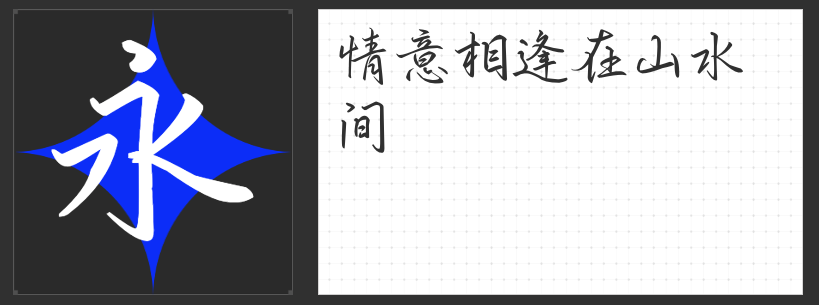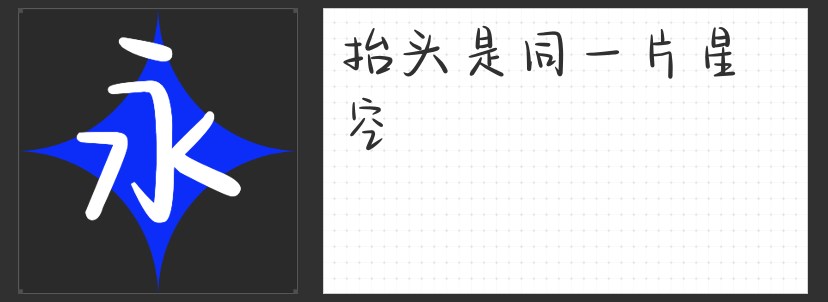
四款电商设计“吸睛利器”:用字体打造视觉记忆点
在电商设计竞争激烈的当下,字体的选择往往成为品牌差异化与视觉吸引力的关键。一款兼具个性与辨识度的字体,不仅能强化信息传递,更能传递品牌调性。以下四款风格迥异的字体,以独特的设计语言为电商设计注入新鲜灵感。
一、字恋狂饼干棒简 粗体
这款字体的设计灵感源自“饼干棒”的随意拼接,笔画分布跳脱传统框架,以圆润、不规则的形态构建字形。例如“圆”字的外框以一笔画出,开口设计形成倒梯形结构,既保留汉字识别度,又赋予无厘头的可爱气质。其粗体设计强化了视觉冲击力,适合作为促销标题或品牌主视觉,尤其契合年轻化、潮流化的消费场景,能快速拉近与用户的距离。
二、字恋狂漫野 鸣风
以手写感为基底,通过直线组合与布白控制,打造出“张弛有度”的动态节奏。笔画去钩处理与局部断开设计,弱化了机械感,灰度均匀的直线结构则确保了远距离识别的清晰度。这种“有序的随意”使其适用于电商首页的模块标题或产品分类标签,既能传递自然亲和力,又能维持版面的整洁感,适合追求品质感与艺术性并存的品牌。
三、字圈也字江月令行楷
行楷字体融合楷书的严谨结构与行书的连笔意趣,左勾竖的出锋设计增添了几分洒脱魄力。其笔画游丝引带,既保留书法韵味,又符合现代阅读习惯,适合作为高端电商的品牌标语或文化类产品标题。在强调传统工艺或国风美学的场景中,这款字体能以“慢节奏”的优雅感,传递品牌的文化深度与价值认同。
四、字圈也字综艺花字体
横斜竖直、折笔钝角与直角交替的设计,赋予字体强烈的几何张力;棱角的圆润与尖锐对比,则暗喻“刚柔并济”的个性态度。其自信的笔画走向与视觉重心偏移,适合运动品牌、潮牌或科技类电商的标题设计,能快速传递“突破常规”的品牌精神,激发年轻用户的情感共鸣。
从萌趣到文化,从秩序到态度,这四款字体以多元风格覆盖不同品类的电商需求。选择与品牌调性契合的字体,不仅是视觉层面的升级,更是与用户建立情感连接的隐形桥梁。